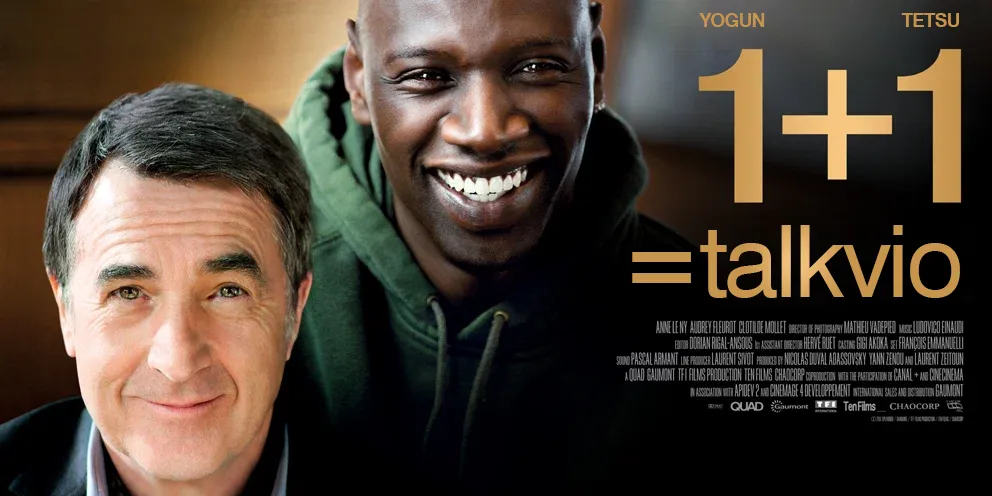
toichiliki, как просила, сделал постер «1+1». Как думаешь «сколько на этом можно срубить?»
Теперь по теме. Создатели «Неприкасаемых» явно использовали простой, известный и стильный шрифт. Надпись одновременно походит на шрифт Helvetica и Swis721. Взяв любой из этих шрифтов и поигравшись с размерами букв и расстоянием между ними можно добиться 100% попадания в постеровский вариант.
Я и думала, что в постере использовано что-то максимально простое
Да, тоже так думал. Постер из разряда "просто, но стильно"